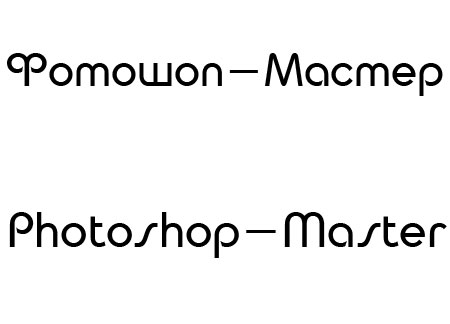
Классный шрифт. Работает на обоих языках отлично
Шрифт классный, но вот буква "в" меня бесит, маленькая "в" выглядит как большая "в" :(
Кругленький такой. Спасибо!